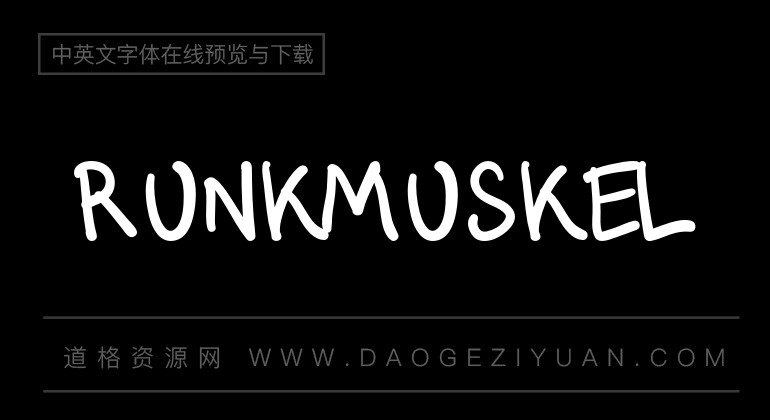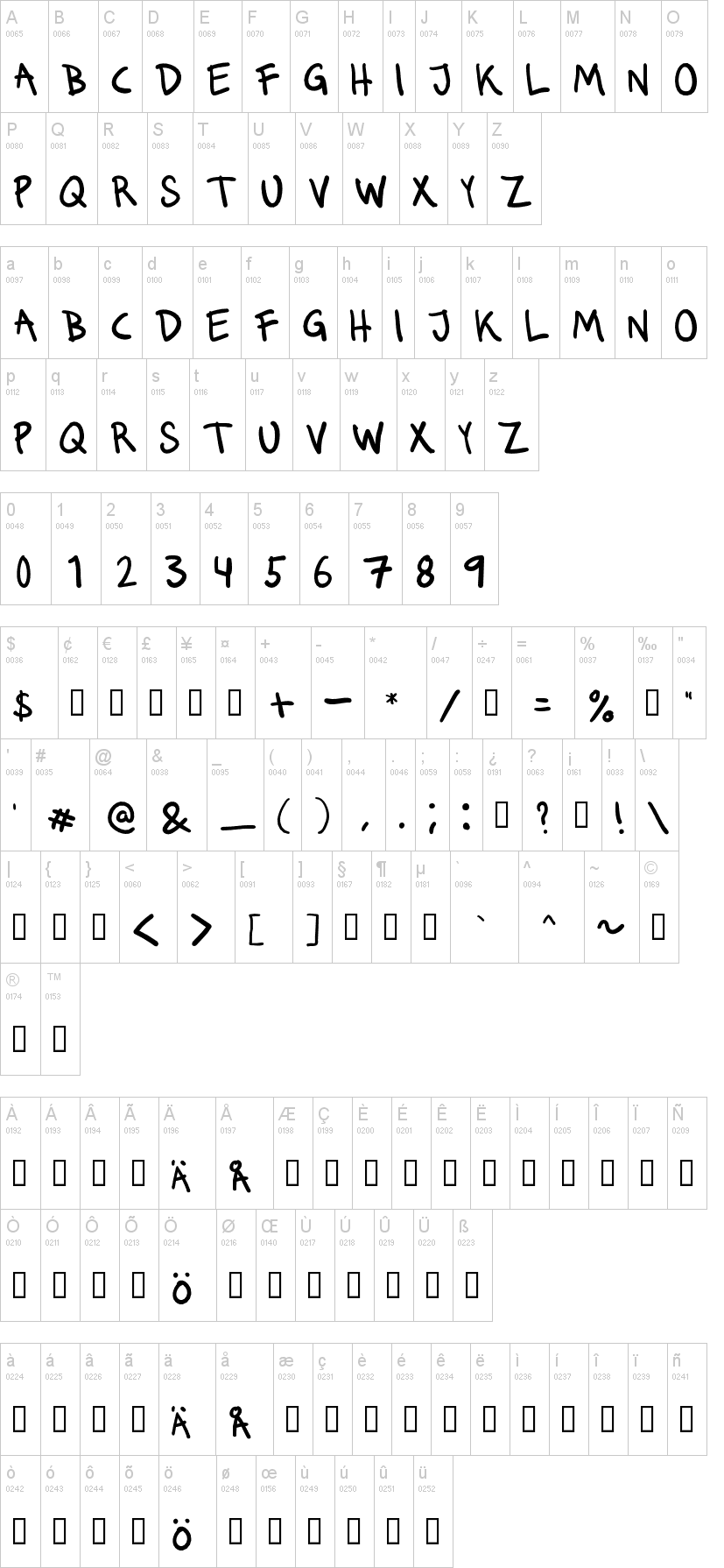
Runkmuskel 是一种由丹麦设计师 Kristian Høgsberg 创建的字体。该字体具有简洁明了的线条,具有现代感,同时又保留了传统的字体特征。它的字形具有良好的可读性,可以用于各种文字和标题。它的特点是字母间距较大,可以让文字看起来更加清晰。Runkmuskel 还具有优秀的细节处理,可以帮助您传达设计的精确信息。内容介绍
Runkmuskel是一款非常不错的手写艺术字体,具有很好的视觉感,适合于文化类的宣传设计、商业类品牌的广告和产品包装设计以及个性化文字排版等较多场景。